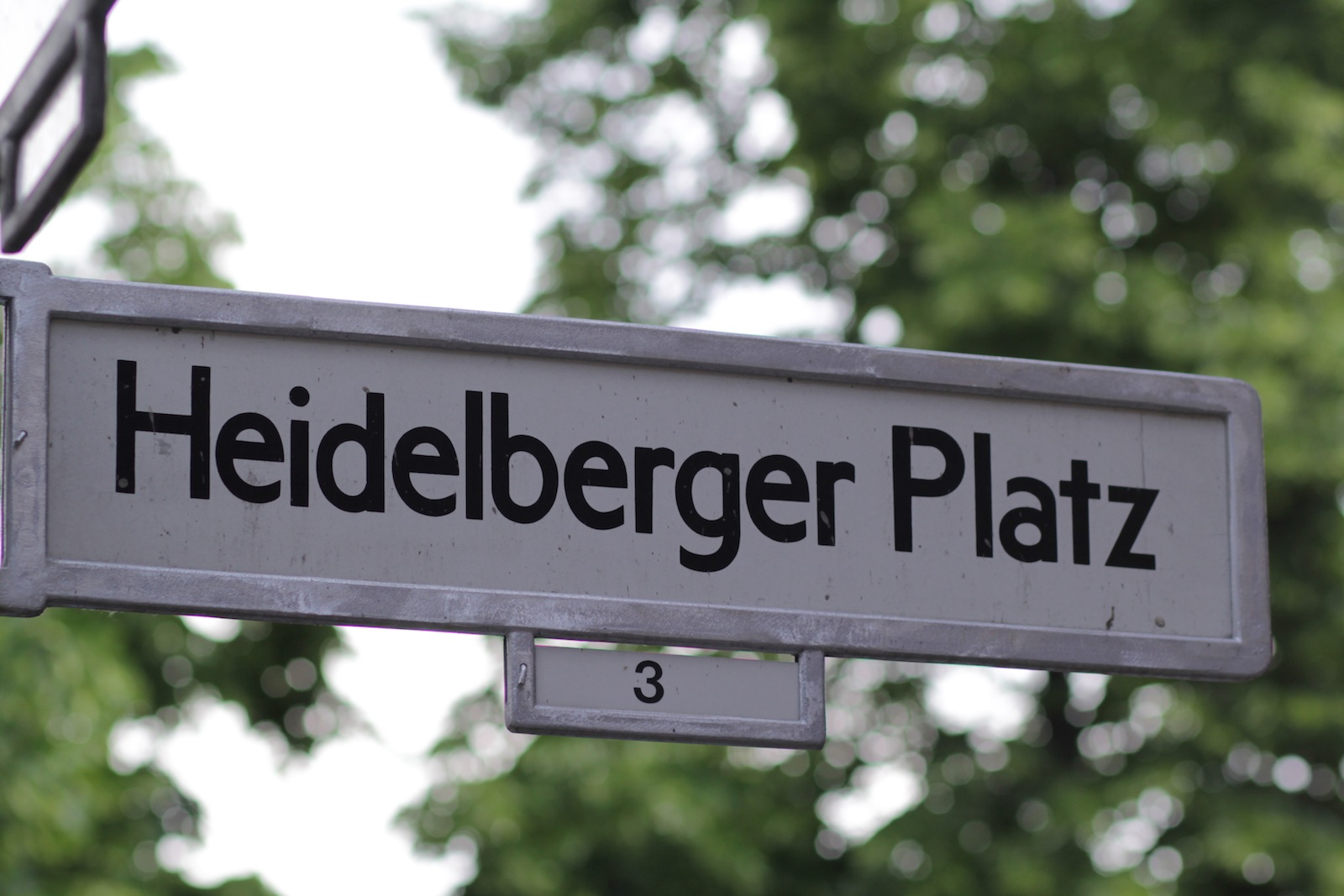
Heidelberger Platz
Straßennamen in Berlin. Ole Schäfer and Verena Gerlach haben sie dokumentiert und daraus die Schriftfamilie FF Cst Berlin West für FontFont kreiert. Ein Artikel und Beispiele finden sich auf FontFont.